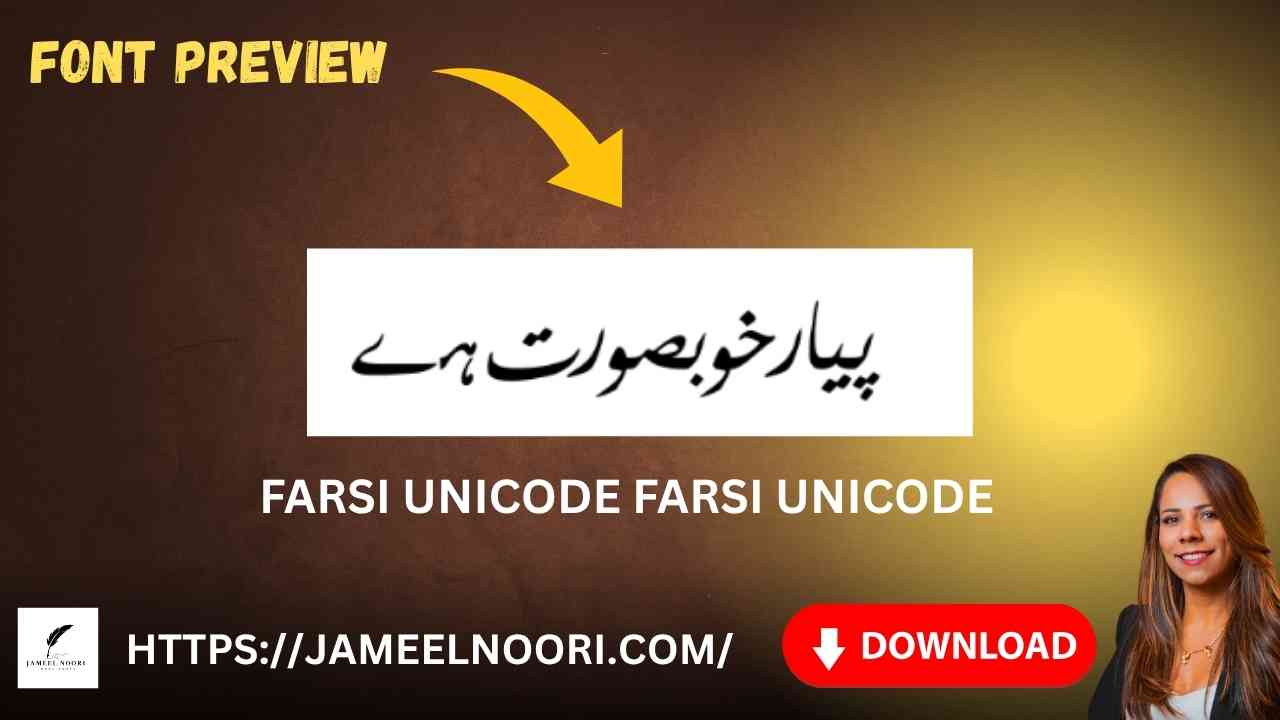
Agar aap Urdu aur Farsi likhne ke liye ek stylish aur Unicode compatible font dhoond rahe hain, to Download Urdu font Farsi Unicode aap ke liye best choice ban sakta hai. Ye font specially un users ke liye hai jo InPage, MS Word, ya web platforms pe Urdu likhna chahte hain Unicode format mein.
Download Urdu font Farsi Unicode – Kya Hai Ye Font?
Download Urdu font Farsi Unicode ek TrueType Unicode font hai jo ke Urdu aur Farsi languages ke liye optimized hai. Iska style simple aur readable hai, jo isay ideal banata hai for digital writing and documentation.
Style | Unicode Urdu + Farsi |
Download Urdu font Farsi Unicode – Key Features
Aaiye dekhein ke is font mein kya khas baat hai jo isay itna useful banati hai:
Main Features:
- Seamless writing experience in Urdu and Farsi
- Clean aur readable character mapping
Download Urdu font Farsi Unicode – Use Cases in Pakistan
Is font ka use aap bohot si situations mein kar sakte hain: